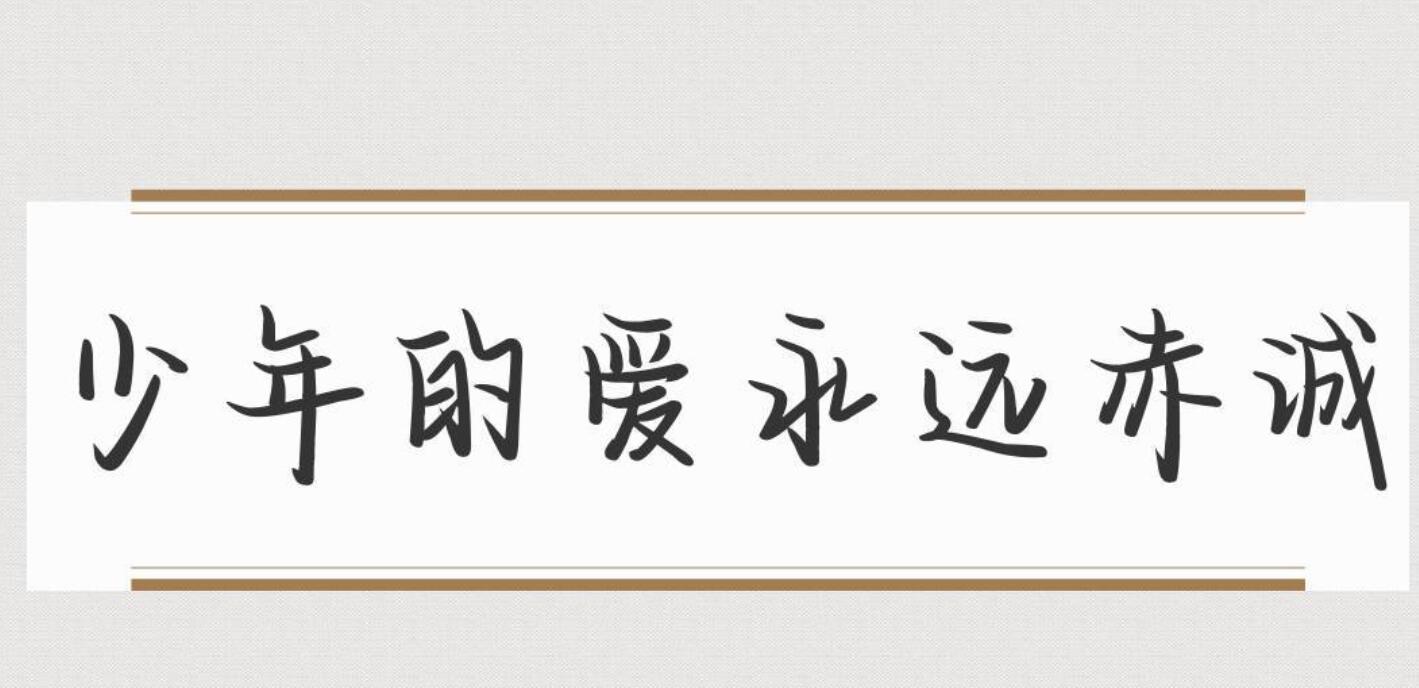
少年的愛永遠(yuǎn)赤誠(chéng),是文道字庫(kù)推出的一款非常不錯(cuò)的藝術(shù)字體,連貫字跡顯得干練而不凌亂,清新簡(jiǎn)明,具有很好的視覺感,適合應(yīng)用于藝術(shù)設(shè)計(jì)、平面宣傳設(shè)計(jì)、網(wǎng)頁設(shè)計(jì),書法字帖等領(lǐng)域,歡迎喜歡冬日限定草莓字體的朋友前來下載使用.